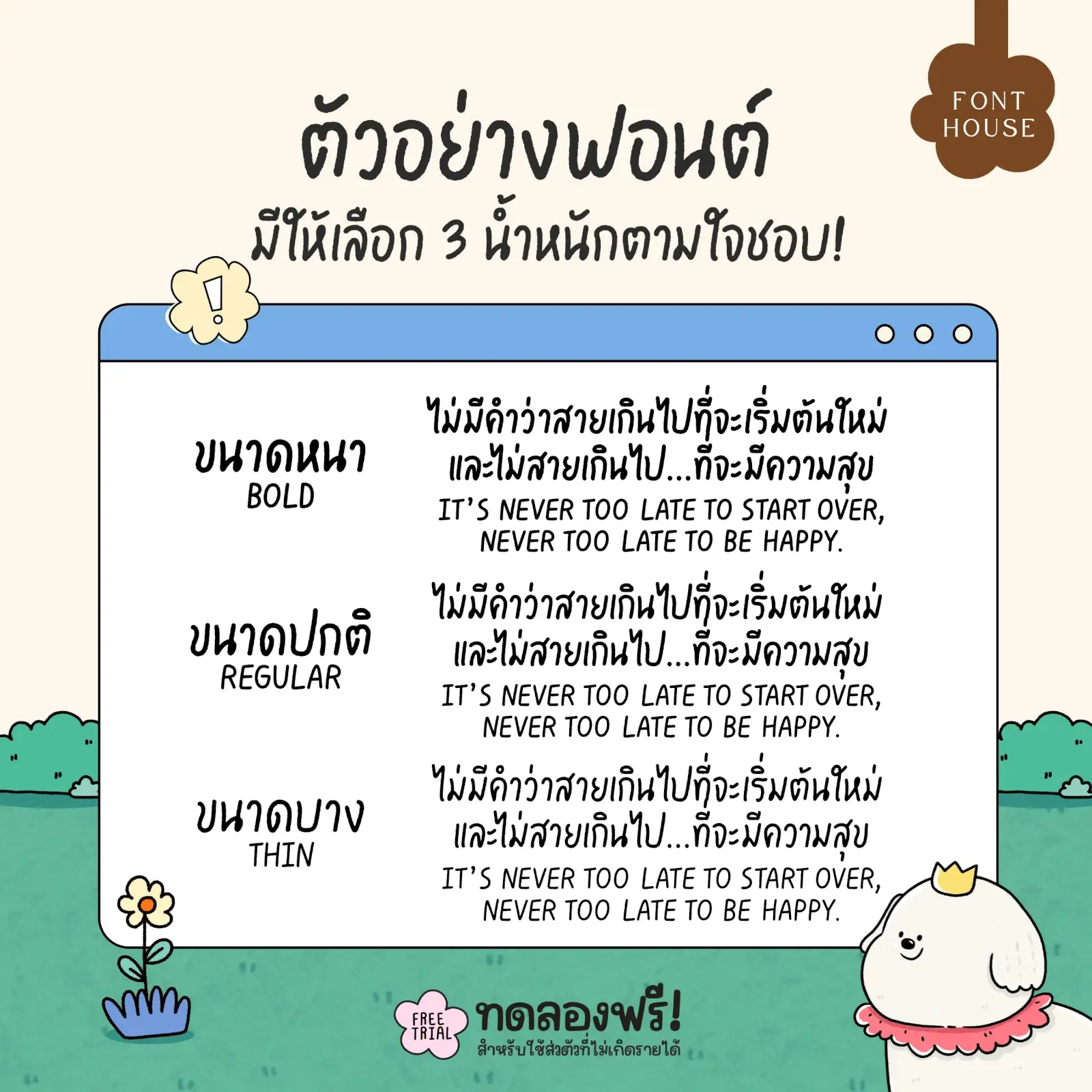
ฟอนต์แฮนด์เมด (FH Handmade) – ฟอนต์ลายมือสไตล์มินิมัล ลายเส้นเป็นธรรมชาติ ดูเหมือนเขียนด้วยมือจริง น่ารัก อบอุ่น เป็นกันเอง และใช้งานได้หลากหลาย “บางครั้ง…งานที่น่าจดจำ ไม่ได้เกิดจากความสมบูรณ์แบบ แต่เกิดจากลายเส้นที่มีตัวตน”
- มี 3 น้ำหนัก
แฮนด์เมด (FH Handmade)